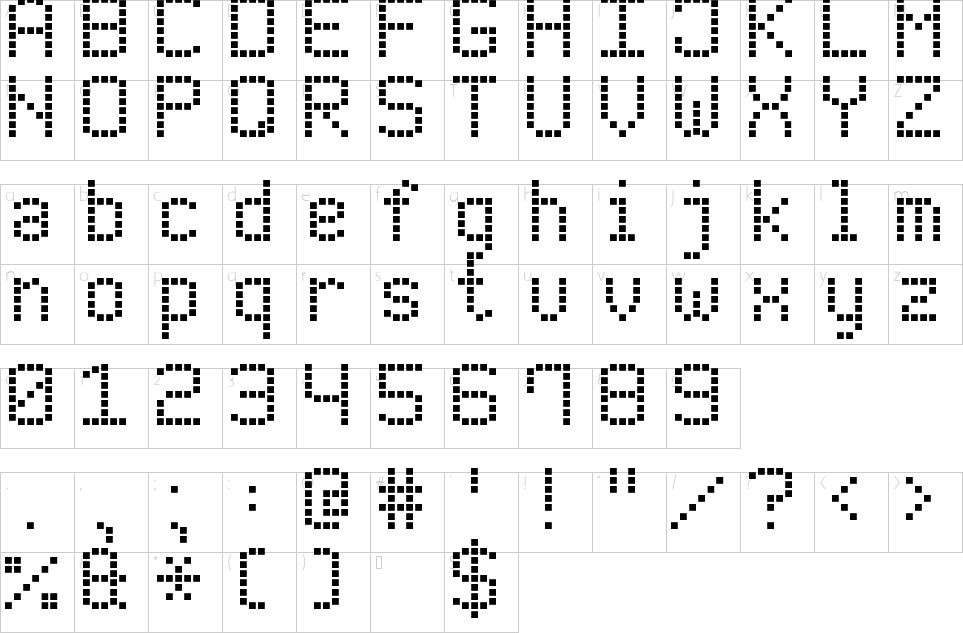
A Modern LED Board 7 é uma fonte minimalista e futurista que se destaca entre as demais. Desenhada pelo estúdio Style-7, essa fonte expressa um estilo moderno e funcional ideal para uso em ambientes digitais. Suas linhas simples e geométricas criam um efeito visual vibrante, perfeito para aplicativos de mídia, design de interfaces de usuário ou qualquer design onde um efeito de LED digital seja desejado. Com seu design limpo e sua facilidade de uso, a Modern LED Board 7 é uma opção versátil para designers digitais e web developers que buscam uma fonte única e moderna. Seu design é baseado na ideia de um painel de LED, característica que a torna um elemento inovador e funcional para qualquer projeto. Com sua presença forte e capacidade de personalização, a Modern LED Board 7 é uma ótima escolha para criar design único e interativo.